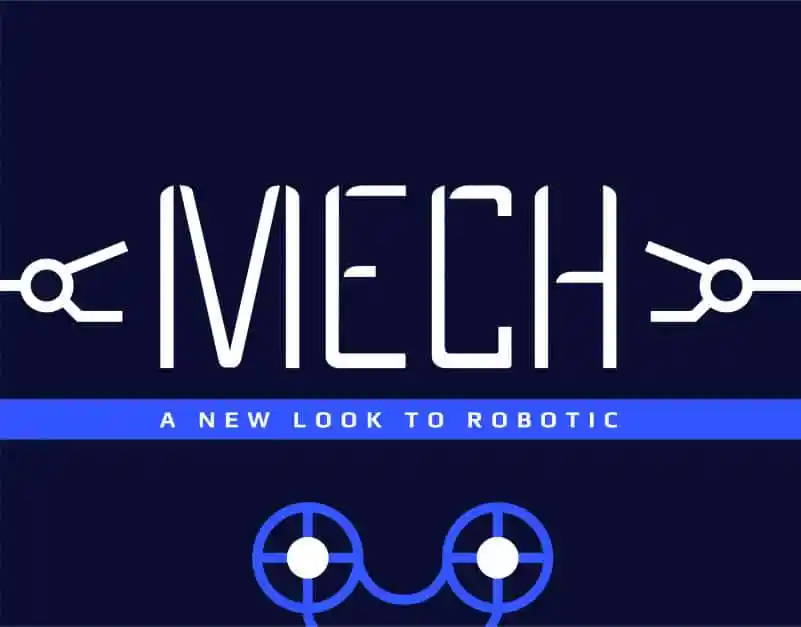
Mech Display Font – Fonte Grátis
Mech Display Font
A fonte ‘Mech Display Font’ é uma tipografia geometrica inspirada nos robôs e tecnologia, criada para atender os olhos enquanto proporciona uma experiência agradável ao contrário de outras fontes stencil. Desenhada especificamente para ser usada em títulos e subtítulos, esta fonte apresenta um toque de sofisticação na sua forma geométrica que se encaixa perfeitamente com o design futurista e revolucionário da tecnologia moderna. Seja você designer, criador ou ilustrador, a font ‘Mech Display Font’ é uma escolha ótima para qualquer projeto que exija um toque de elegância e sofisticação em seus títulos visuais. Ela se destaca por sua facilidade de leitura, oferecendo um design que combina funcionalidade com estilo, tornando-se o parceiro perfeito para quem procura uma fonte que ressoa claramente nas ondas modernas da tecnologia e design digital.